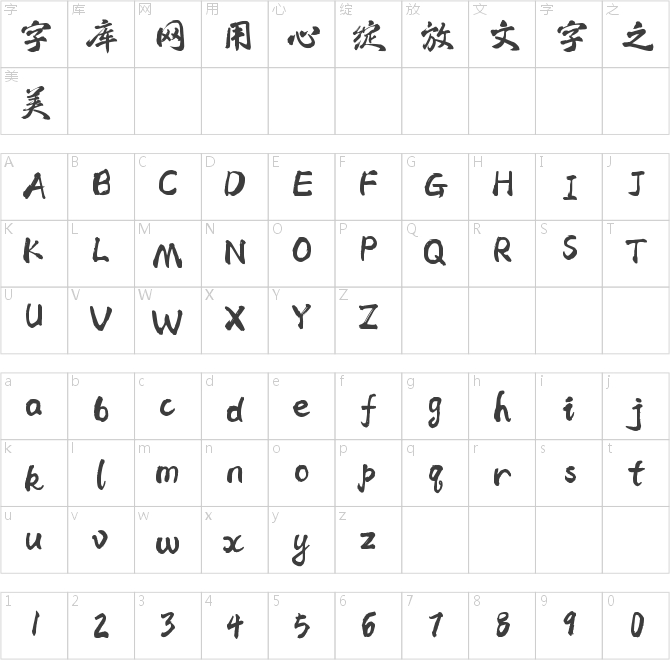
字魂215號-清平手書
字魂215號-清平手書是一款書法字體。字體的行筆自然,部分筆畫之間留下了相互牽連,字體顯得迅捷流暢,字體的風格舒展灑脫,適用于文化類的宣傳設計,商業的品牌廣告和產品包裝設計。
字魂215號-清平手書字體zihun215hao-qingpingshoushu字庫是一款讓人賞心悅目、百看不厭的中文字體,適合各類廣告和產品包裝設計應用,字體大小18.3MB,格式為ttf字體,上傳用戶是鯨魚只會打狙,作者/版權方為字魂